免费字体下载 管理自己的企业是一项耗费精力的工作。如果您的小型企业中没有常驻设计师,那么在改造公司网站或设计宣传海报时,在字体的选择方面,可能会不知所措。选择一款的漂亮的字体对您的宣传至关重要,但许多小企业主没有专业的设计师。
在下载免费字体之前,你需要知道的事情就是,什么是 serif 字体与 sans-serif 字体。serif 衬线字体在每个符号的主要笔画末端都包含装饰性的装饰。另一方面,sans-serif 无衬线字体则不然。
您无需花钱购买商业字体,就可以免费下载一套精美的衬线字体。下面汇总了 20 种免费衬线字体的列表,这些字体是由该领域的一些知名的设计师设计的。
这些装饰出现在 Times New Roman 或 Courier 等流行字体中,从视觉的角度来看,使文本更自然地流动。这意味着,尤其是在印刷形式中,衬线字体通常更容易阅读。
1.免费字体下载 Merriweather Serif
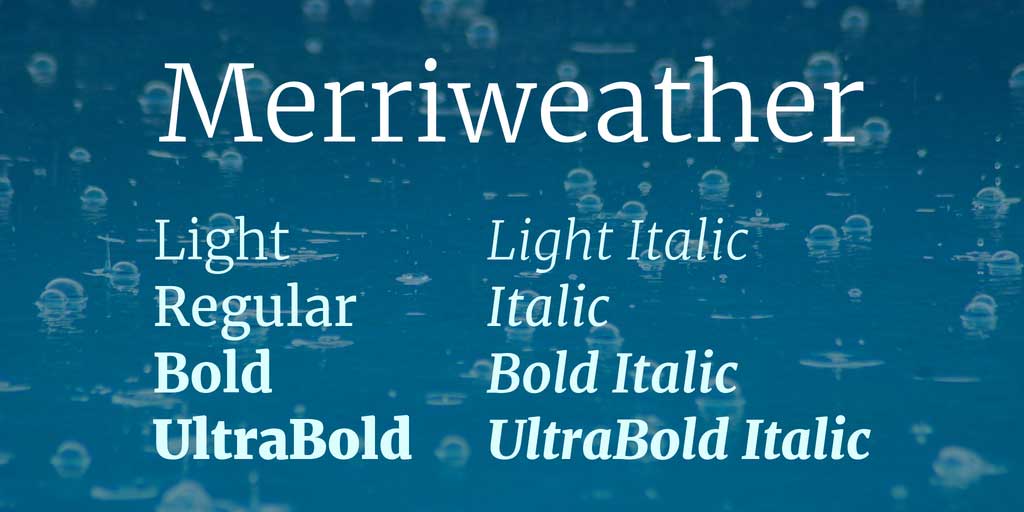
Merriweather Serif 字体由Sorkin Type Co 的Eben Sorkin设计,是一种高度通用的 serif 字体,即使在移动设备上也具有最大的可读性。
如果您希望从智能手机访问您的主页,Merriweather Serif 字体具有坚固的设计和相当大的 x 高度,给人留下持久的印象。
2. 免费字体下载 Modum
Modum由Jonathan Hill设计,是我们最喜欢的现代衬线字体之一。文字表面具有低对比度,能够融合传统曲线和形式,同时保持现代使用的实用性。
如果您的公司定期生成编辑项目,请考虑将 Modum 设为您的新备用字体。
3.免费字体下载 Arctic
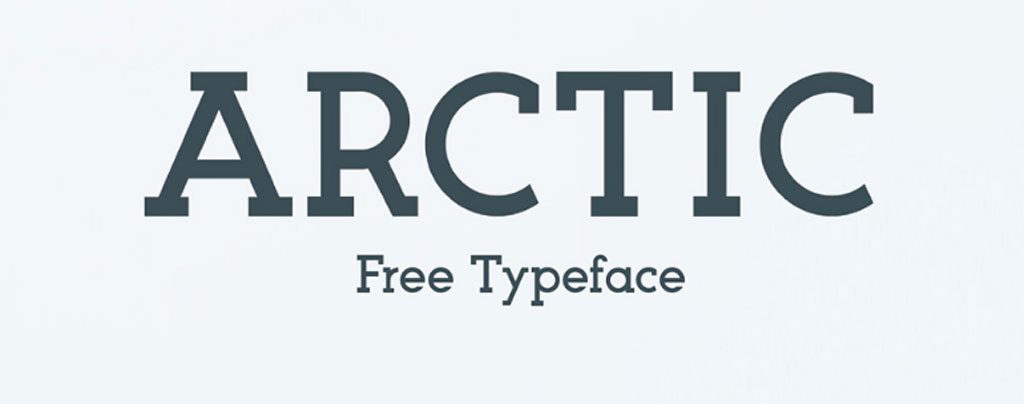
与更传统的衬线字体不同,Arctic 充满了标志性的字符和现代风格,适合在家中推广户外生活方式产品或具有同等技巧的地下音乐表演。由Matt Ellis设计,Arctic 是一种带边缘的平板衬线字体。
4.免费字体下载 Cinzel
Cinzel 是一个重新构想的起源故事,采用一世纪罗马字母的经典铭文,并为 21 世纪提供时尚的形状和感觉。
由Natanael Gama设计的 Bold、Black、Regular 和 Decorative 变体在数字媒体中表现良好,尽管对比度很高。
5.免费字体下载 Droid Serif
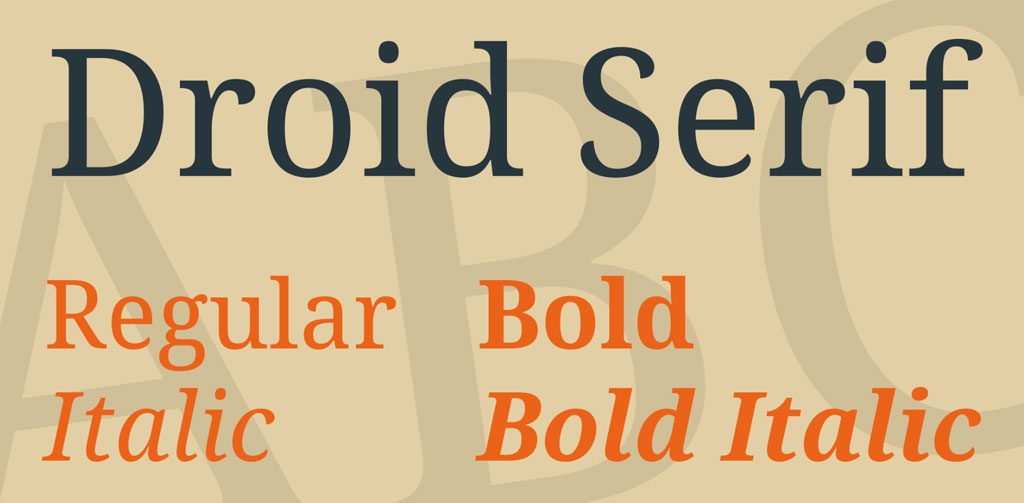
Steve Matteson设计了 Droid Serif,这是一种必不可少的现代衬线字体,经过浓缩可以增加您的移动网站在屏幕上可以容纳的文本数量。
真正的网络衬线字体,Droid Serif 坚固的构造和开放的形式使不存在的价格标签令人惊喜。
6.免费字体下载 Tryst
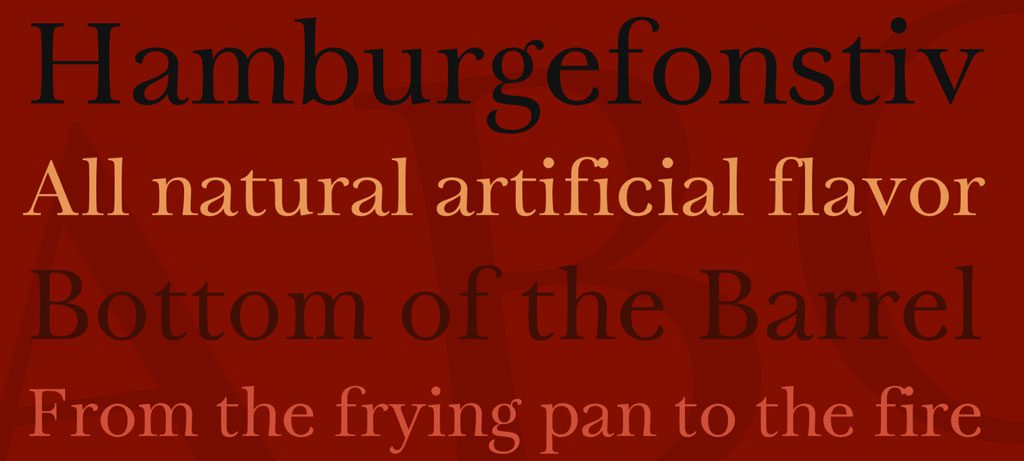
Philatype设计了这款优雅的字体,从 18 世纪的过渡字体中汲取灵感。Tryst 可以被归类为一种柔软而诱人的字体,它仍然可以提供清晰和可信度。
根据您的品牌标识,Tryst 是您网站和营销材料的重要资产。
7.免费字体下载 Corduroy Slab
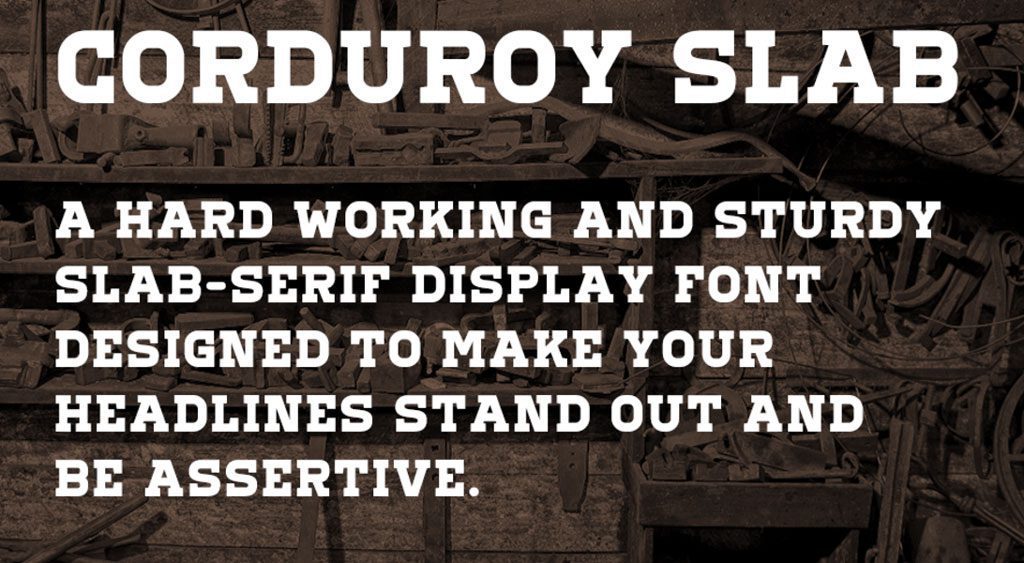
专门设计为标题字体,企业主可能认为 Corduroy Slab 不如其他衬线字体通用,因为字体是全大写的。但如果有正确的审美,Ryan Welch的这款字体可以给消费者留下不可磨灭的印象。
8. 免费字体下载 Voga
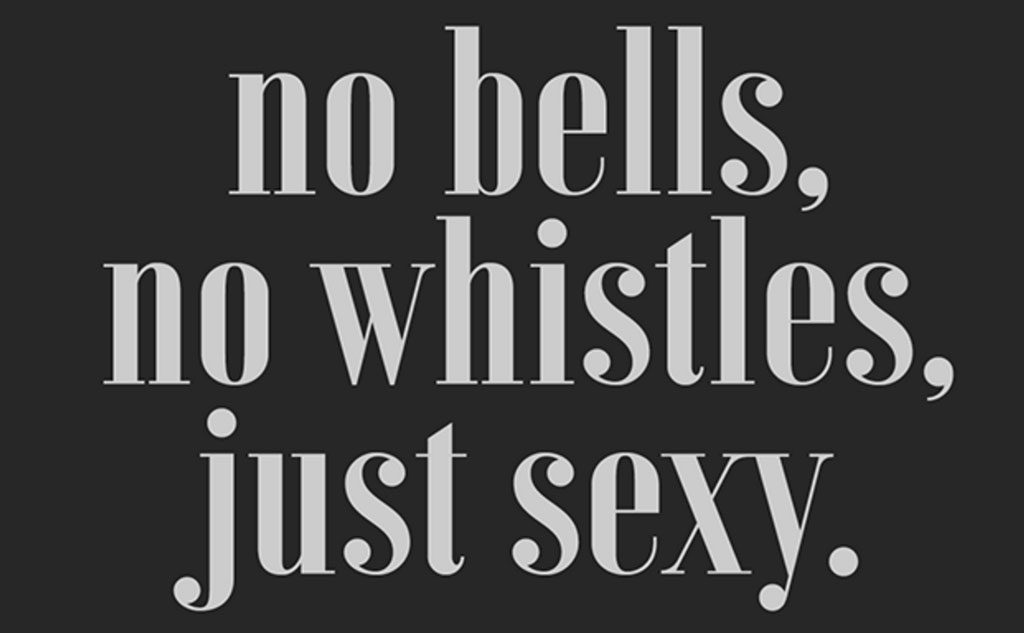
设计师Charles Daoud在设计 Voga 系列字体时有一个明确的目标:一种性感的字体,可以让任何单词组合看起来都很迷人。
9.免费字体下载 Ayres
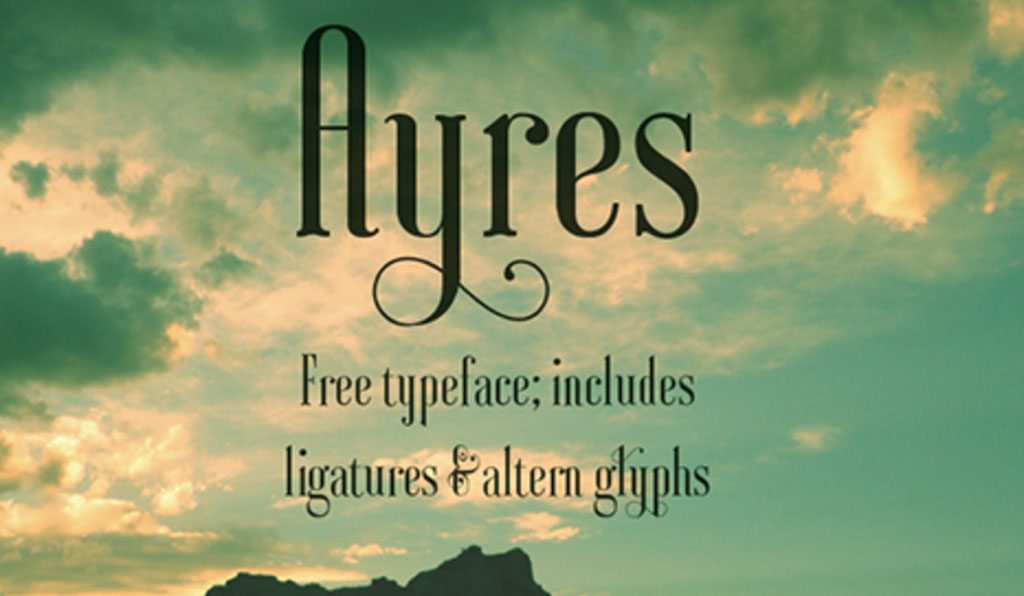
这些字体中有许多是衬线字体,在某种意义上是为数字使用而设计的,但 Ayres 是一种令人愉悦的字体,最适合用于邀请、服装设计、产品包装、海报或任何标识设计项目。Ayres 由设计师Mariel Gornati设计。
10.免费字体下载 Hagin
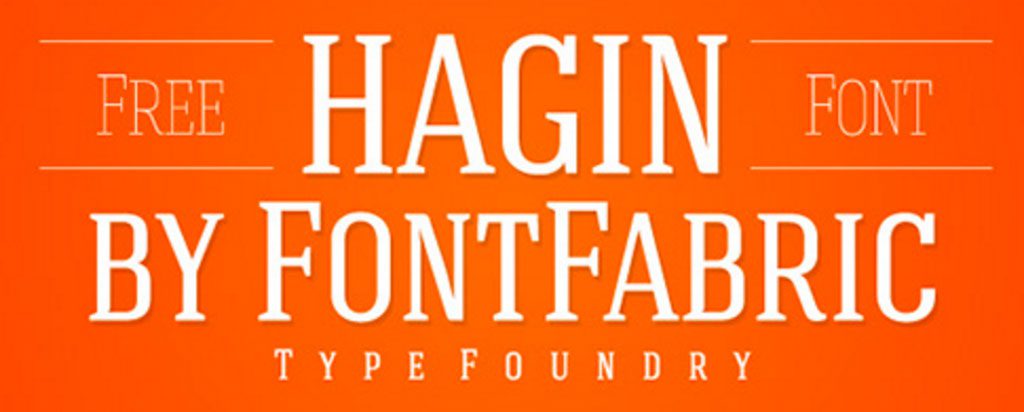
Fontfabric围绕强大的几何形式构建了 Hagin 字体,为小企业主提供了用于 T 恤、海报和徽标的醒目字体。
哈金看起来毫不费力地专业而不闷。如果您想让您的信息一目了然,请选择 Hagin。
11.免费字体下载 Abraham Lincoln Serif
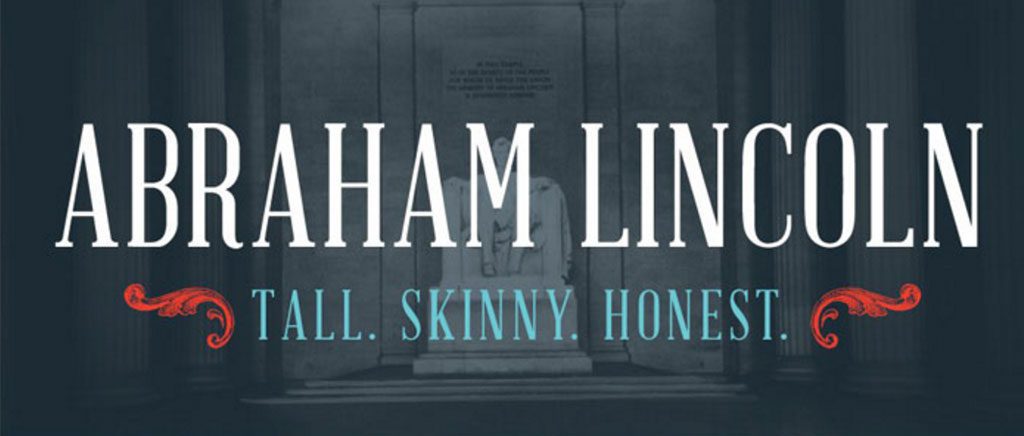
如果这个名字本身不吸引你,考虑一下:设计师Frances Macleod创造了这种字体来反映我们第 16 任总统的身体属性,口号是“Tall. 瘦骨嶙峋的。诚实的。”
12.免费字体下载 Lovato
Lovato 系列字体由Philatype 的Kosal Sen设计。Lovato 最大的特点之一是它在最轻和最重的重量之间的情绪范围,从微妙到主导。
大多数几何形状的 Lovato 是海报设计、书籍封面和一般品牌的绝佳选择。
13.免费字体下载 Brela
当您在寻找编辑衬线字体时,请始终将 Brela 放在您的后袋中,即使是非常小的尺寸也完全清晰易读。
当小细节清晰可见时,这种人文主义衬线字体就会变得活跃起来,这使得 Brela 成为标题和页面标题的明显选择。Brela 由Makarska Estudio设计。
14.免费字体下载 Agne
Ricardo Ponce(专业称为Cargoneblina)设计了这种引人注目的高对比度字体,可以根据上下文在重和轻之间摇摆不定。
Agne 是用于名片、海报和其他需要一些魅力的专业印刷品的恒星字体。
15.免费字体下载 Akura Popo
Akura Popo 是Twicolabs Design最近推出的一种字体,它是一种高度浓缩的衬线字体,依靠复古设计来传达一种硬朗的粗犷感。
显然,您会希望避免在登录页面的正文中使用这种衬线字体,但对于正确的品牌,Akura Popo 可以作为信笺、徽标或标题文本发挥神奇的作用。